War die Neue Typografie wirklich so neu?
Beim Begriff »neuer Typographie« denken wir an Tschichold, bauhaus und das weitere Umfeld. War das in der Zeit der 20er Jahre wirklich so dominant und tatsächlich bestimmend? Liest man beispielsweise in den Biografien von großen Verlegern des 20. Jahrhunderts oder befasst sich mit der Geschichte der Druckereien so ergibt sich ein differenzierteres Bild. Wer war bestimmend für den Typographischen Stil dieser Zeit? Müssen wir umdenken?
Julia Meer, eine praxiserfahrene Kommunikationsdesignerin, geht in ihrer Dissertation diesen Fragen nach. »Während die Neuen Typographen als Künstler zweifellos Avantgarde waren, lässt sich dies mit Blick auf ihre typographischen Leistungen nur bedingt behaupten ...«, so schon in der Einleitung zu ihrem Buch. Die Leistungen der Neuen Typographie gingen eigentlich schon früher von der graphischen Fachwelt aus, wobei die entscheidenden Persönlichkeiten kaum bekannt sind. Diese empfanden die Avantgarde sogar als unmodern und nicht professionell.
Meer prüft das Innovationspotential der Neuen Typografie und kommt rasch zum Ergebnis, dass das Neue der Neuen Typografie nicht so neu war, die Zweckmäßigkeit und Sachlichkeit bei Schriftsetzern längst allgemein üblich war. Daran hatte die englische Reformbewegung spätestens 1910 großen Anteil wobei auch hier schon das Ornament als überflüssig eingestuft wurde und die Persönlichkeit des Gestalters in den Hintergrund treten sollte. Auch der Einsatz von Maschinen wurde bereits befürwortet. Schon 25 Jahre vor Tschicholds Forderungen von 1925 wurde in der Zeitschrift Vers sacrum Mitteilungen in einfachster Form gefordert und auf das Wesentliche reduzierte Sachplakate gab es auch schon.
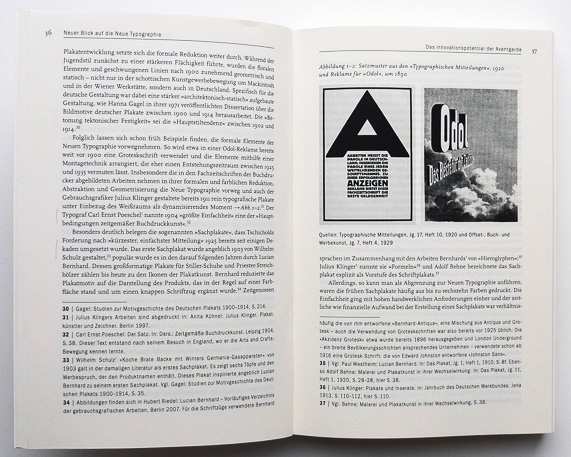
Zudem werden von Julia Meer erhebliche Mängel der Designgeschichtsschreibung festgestellt. Zum Teil haben sich die Gestalter selbst überhöht dargestellt wie Tschichold. Oder euphorische Monografien wurden von den Gestaltern nahestehenden Personen verfasst. Zudem fehlt die Abgrenzung zwischen Kunst und Design. Für das Graphikdesign und die praktische Typografie waren technische Erfindungen oft wichtiger als stilistische Festlegungen oder Strömungen.
Skeptisch betrachteten die Kreise der Buchdrucker, der Werbetreibenden und der Gebrauchsgrafiker die Programme der Avantgardisten und lehnten diese eher ab. Bei allen drei Berufsgruppen geschah dies aus verschiedenen Gründen. Die Buchdrucker hatten selbst schon an Entwicklungen gedacht und wollten sich von Künstlern nicht drein reden lassen, zudem sie die Arbeiten um die Neue Typografie zunächst als unprofessionell empfanden. Den Werbetreibenden war das Revolutionäre zu dogmatisch und zu wenig erfolgsorientiert. Die Gebrauchsgrafiker wollten lieber an »Stimmungen« für Ihre Kunden arbeiten und keine ästhetische Erziehung, wie es die Neue Typografie forderte, beginnen.
Aber schon einige Jahre später änderte sich die Situation indem immer mehr Elemente der Neuen Typografie in die Arbeiten der Mitglieder der einzelnen Gruppen mit einflossen. Die Ablehnung der Neuen Typografie wich einem dynamischen Umgang und einer Integration brauchbarer Elemente. Diese »Domestizierung« der Ideen wurde vor allem von den Fachzeitschriften der Buchdrucker gefördert. Über die Fachkreise hinaus kam die Idee durch Zeitschriften wie die Berliner Illustrierte Zeitung an die Öffentlichkeit, da diese den neuen Stil einsetzten. Tschichold befahl seine Postulate nicht mehr dogmatisch und anerkannte wichtige Fachleute des graphischen Gewerbes wurden mit einbezogen wie Renner, Ehmke, Trump und andere.
Im letzen Kapitel untersucht Julia Meer wie weit sich die Avantgarde professionalisiert hat. Zur Professionalisierung gehören:
- Spezifisches Fachwissen,
- Eine institutionalisierte Ausbildung mit zertifiziertem Abschluss,
- Ein Verhaltenskodex und
- Ein aktiver Berufsverband.
Eine wissenschaftliche Forschungen musste erst aufgebaut werden. Die institutionalisierte Ausbildung ist heute immer noch fraglich, da es nach wie vor Qereinsteiger und Autodidakten gibt. Das Verhalten hängt sehr stark mit der Persönlichkeit zusammen, ist allerdings 1924 mit der Londoner International Advertising Convention schon festgelegt worden. Die Berufsverbände der drei Gruppen waren ohnehin zumindest zum Teil schon sehr aktiv. Das Thema ragt dann auch weit in unsere Gegenwart hinein.
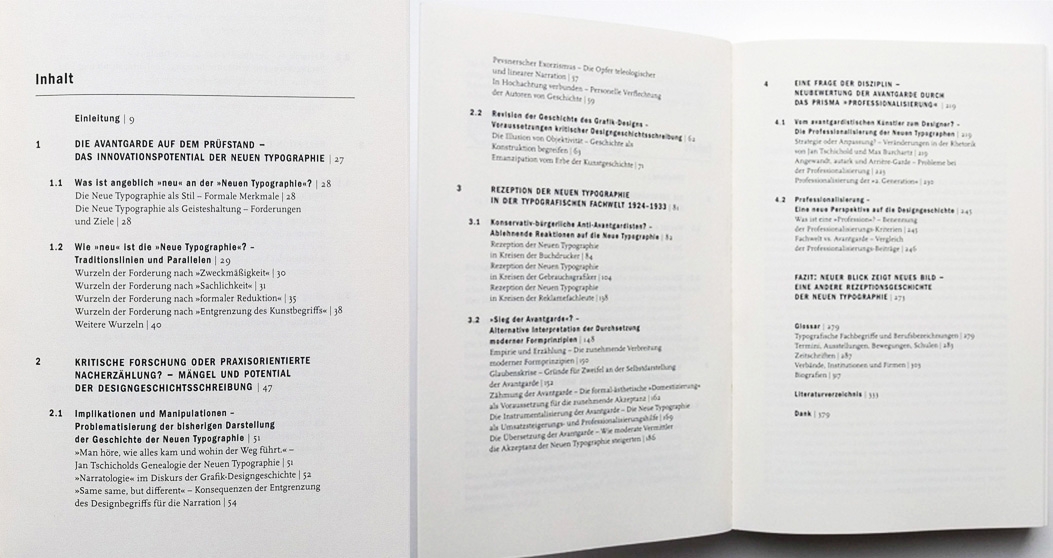
Der Text dieser Dissertation ist klar geschrieben. Wiederholungen lassen sich durch die Recherche- und Forschungsintensität wohl nicht vermeiden. Die Typografie ist angemessen einfach und klar. Es gibt ein umfangreiches und sehr interessantes Glossar (120 Seiten). Leider klammert die harte Bindung, was das Lesen und Arbeiten etwas erschwert.
Julia Meer
Neuer Blick auf die Neue Typographie
Die Rezeption der Avantgarde in der Fachwelt der 1920er Jahre